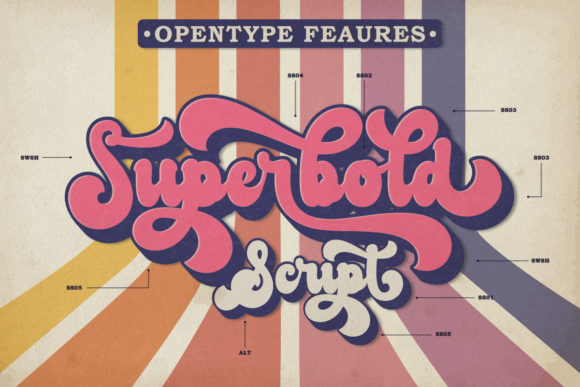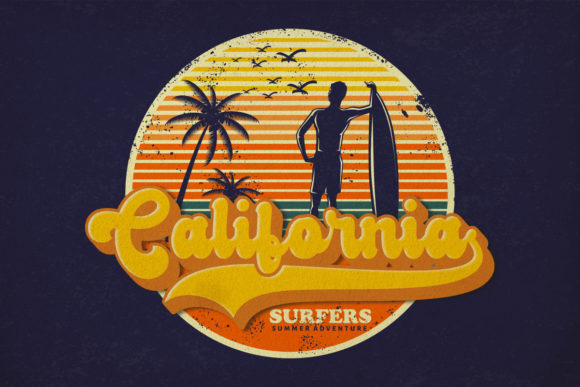
復古粗體英文字體
今天 Creative Fabrica 的限時免費字體是 The Boldstyle ,原價 $21 美元,現在限時 24 小時免費下載,還附帶商業授權。字體充滿復古氣息、帶著 60-70 年代粗體手寫風格的字體。
字型介紹
由印尼設計工作室 Almeera Studio 打造字體,帶有強烈的復古 (Retro) 風格,充滿了 1960-70 年代的嬉皮與迪斯可時代美感。